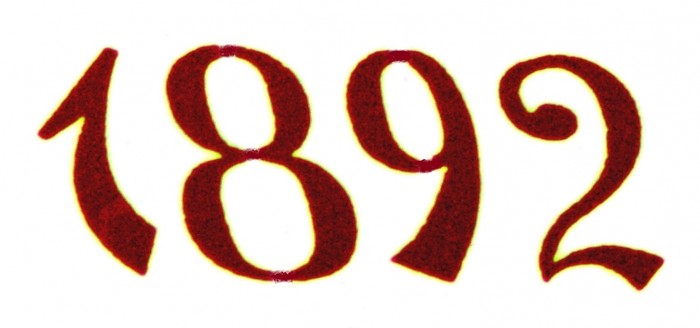
Wetterfahne mit Inschrift des Baujahres 1892, welche Schrift?
Die Wetterfahne hat das Baujahr des Hauses eingestanzt. Ich möchte die gleiche Schrift für  den Hausnamen verwenden.
Üblicherweise wurden zu der Zeit keine Satzschriften für derartige Beschriftungen verwendet. Schon die Form der 1 lässt vermuten, dass die Zahl vom Kunstschmied selbst gestaltet wurde.